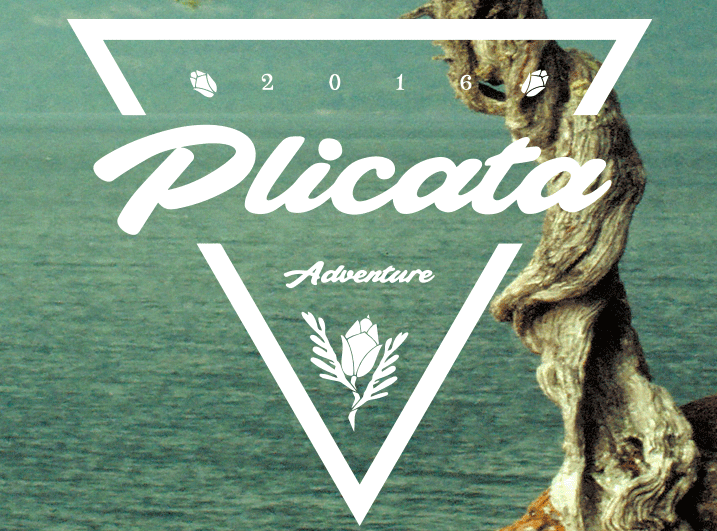
A Plicata é uma fonte criada com mão cheia por Måns Grebäck. Suas linhas script são legíveis e claras, trazendo um toque elegante às suas projetos gráficos. É perfeito para usar em logomarcas de lojas ou sites web, proporcionando uma cara personalizada que destaca seu negócio entre a multidão. Composta com todo cuidado, esta fonte é o escolher-se em qualquer projeto onde você deseja um toque sofisticado e único. Seja para criar logos vívidos, headlines intrigantes ou textos de texto, Plicata está à disposição para fazer sua arte mais chamativa.
Designer: Måns Grebäck